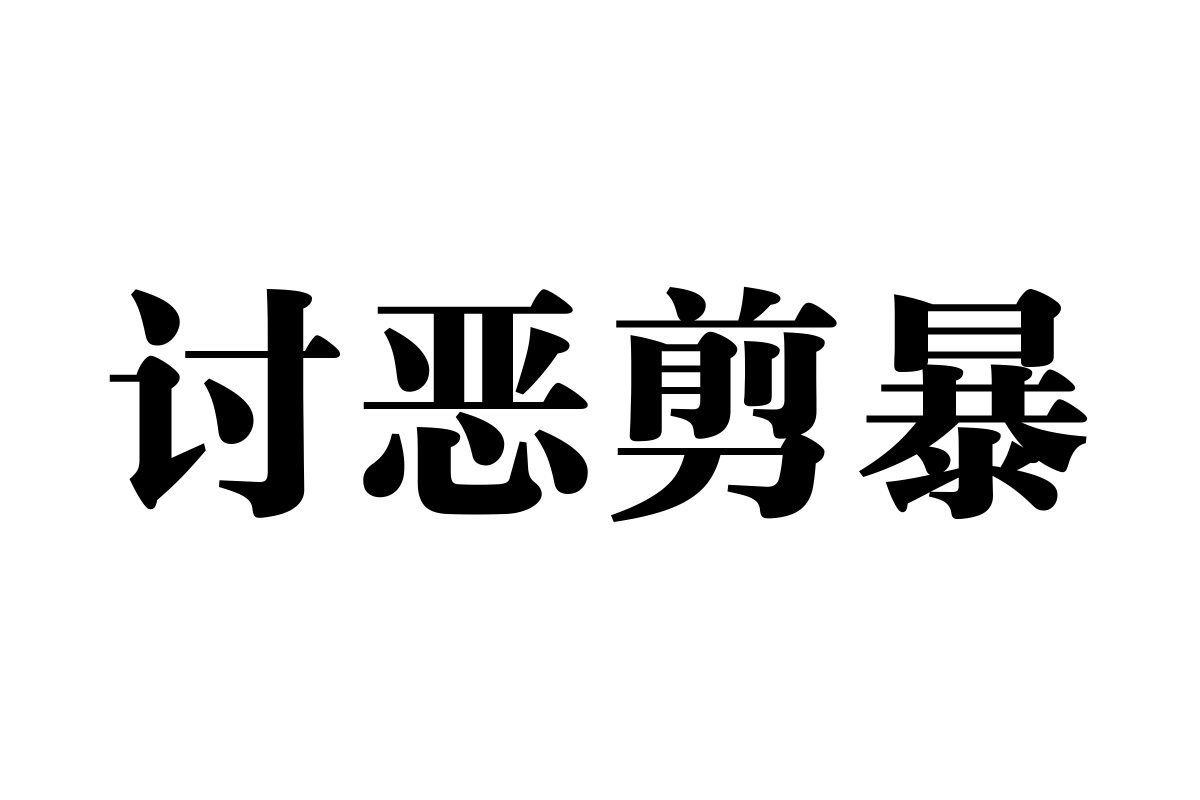
汉仪玄宋 85S 是一款具有独特风格的字体,它采用了现代的设计元素和传统的书法风格相结合的方式,创造出了一种既现代又具有传统韵味的字体。这款字体的特点是字形简洁大方,线条流畅自然,给人一种清晰、易读的感觉。同时,它的笔画粗细变化丰富,既有粗犷有力的线条,也有细腻柔和的线条,能够适应各种设计需求。此外,这款字体还具有一定的艺术性,线条之间的连接和转折都经过精心设计,使得整体视觉效果更加协调和美观。总的来说,汉仪玄宋 85S 是一款非常适合用于标题、正文等场合的字体,无论是在商业还是文化领域,都能够发挥出良好的效果。